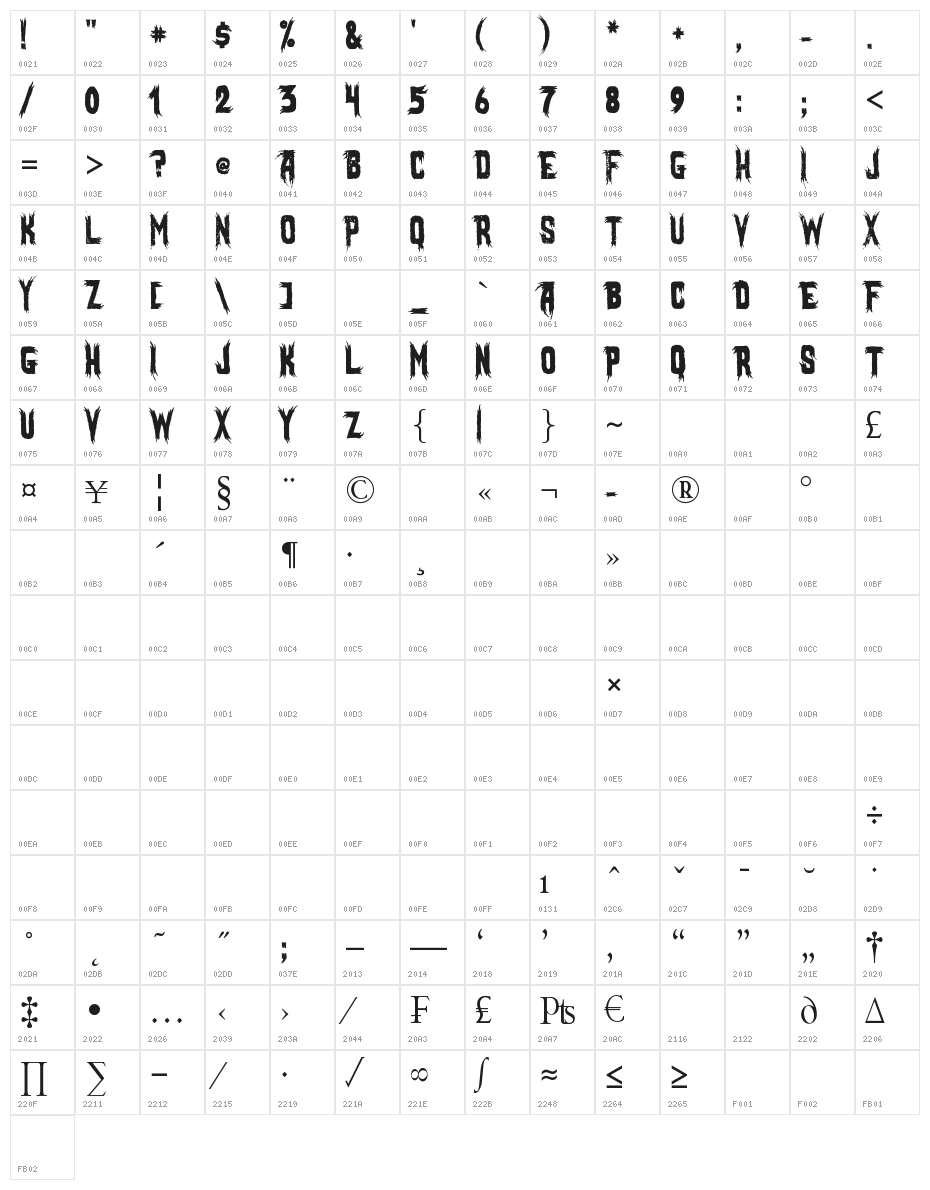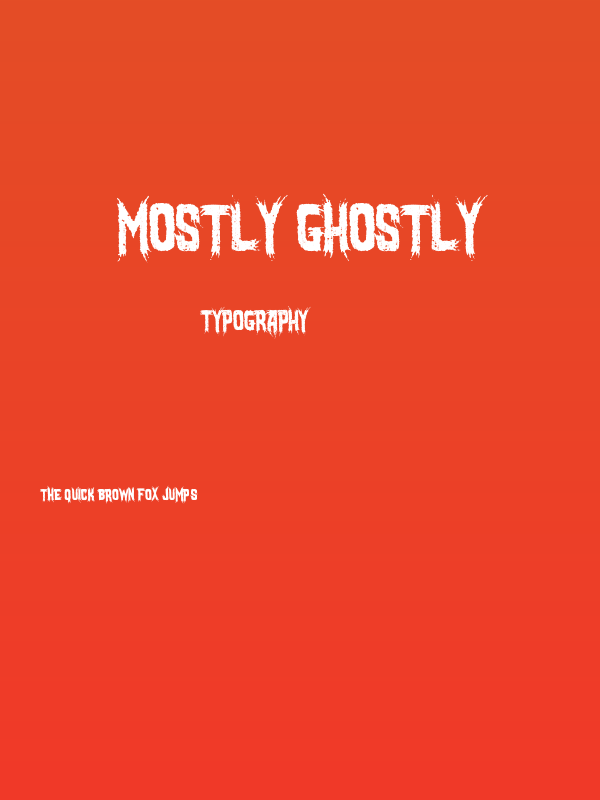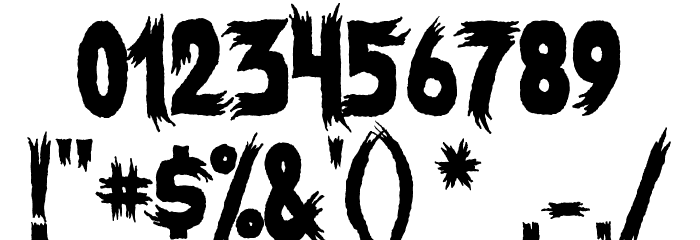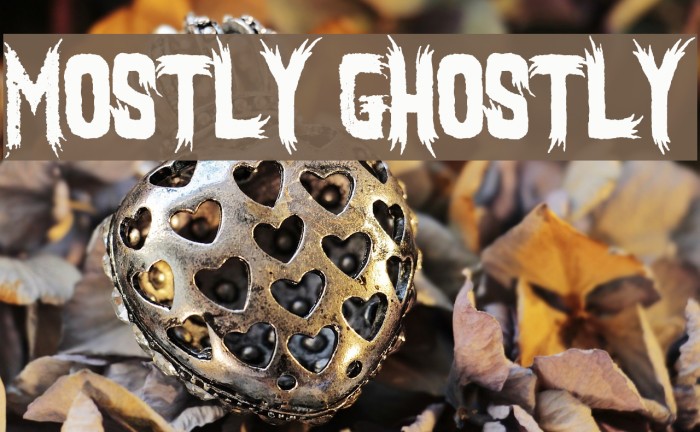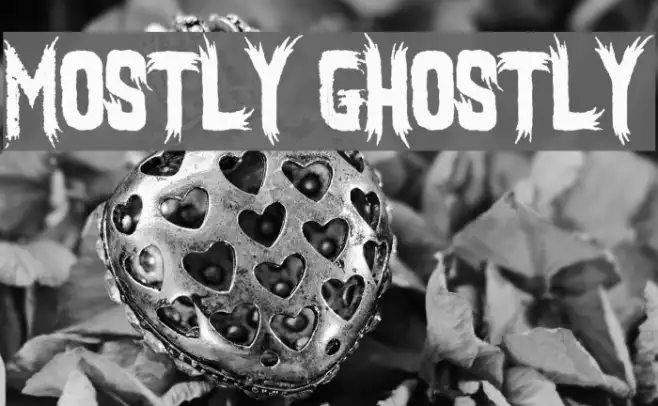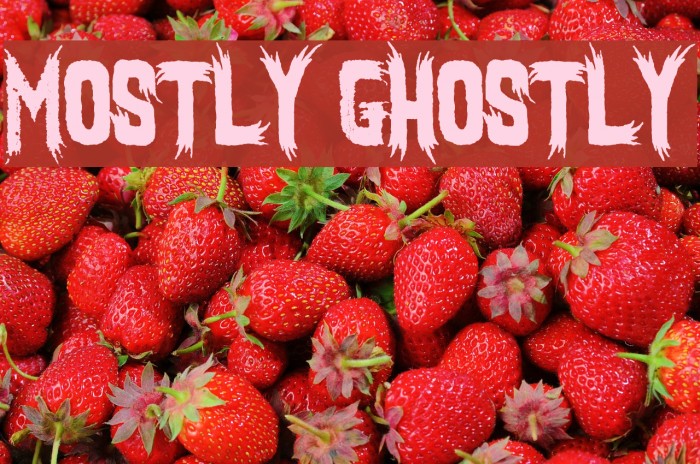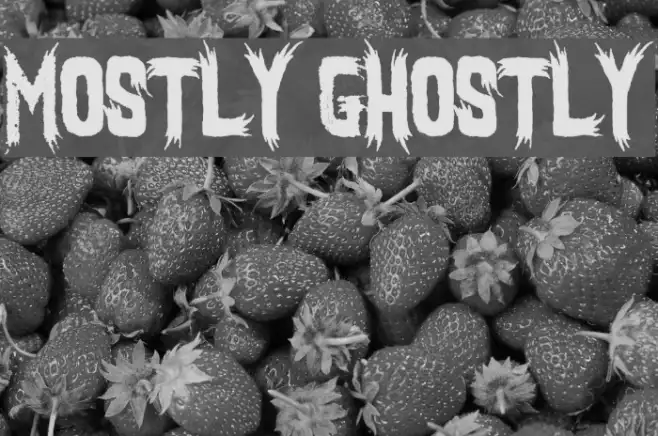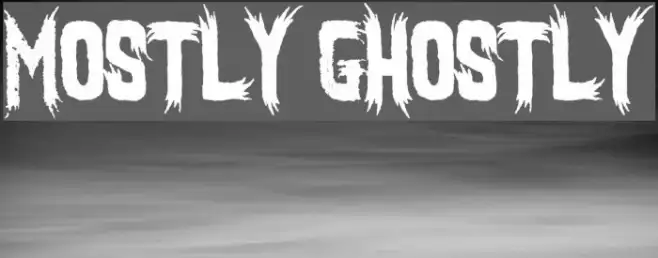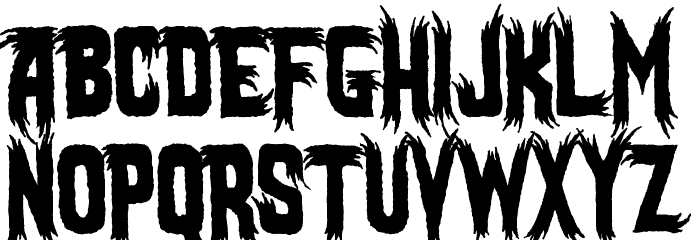
Mostly Ghostly Font
MOSTLY-GHOSTLY MAJUSCULES
MOSTLY-GHOSTLY MINUSCULES
MOSTLY-GHOSTLY AUTRES CHARS
| Projets proposés | Ideal for Halloween-themed designs, horror movie posters, haunted house flyers, and spooky event invitations. |